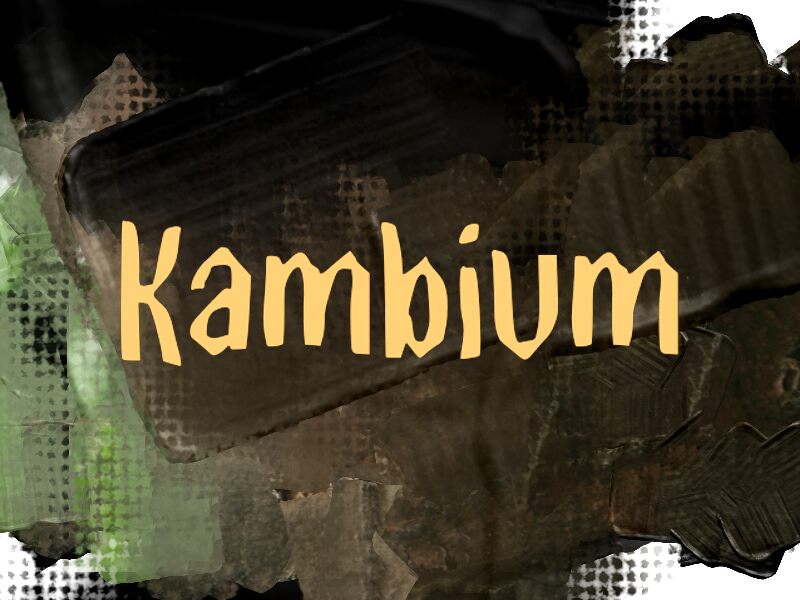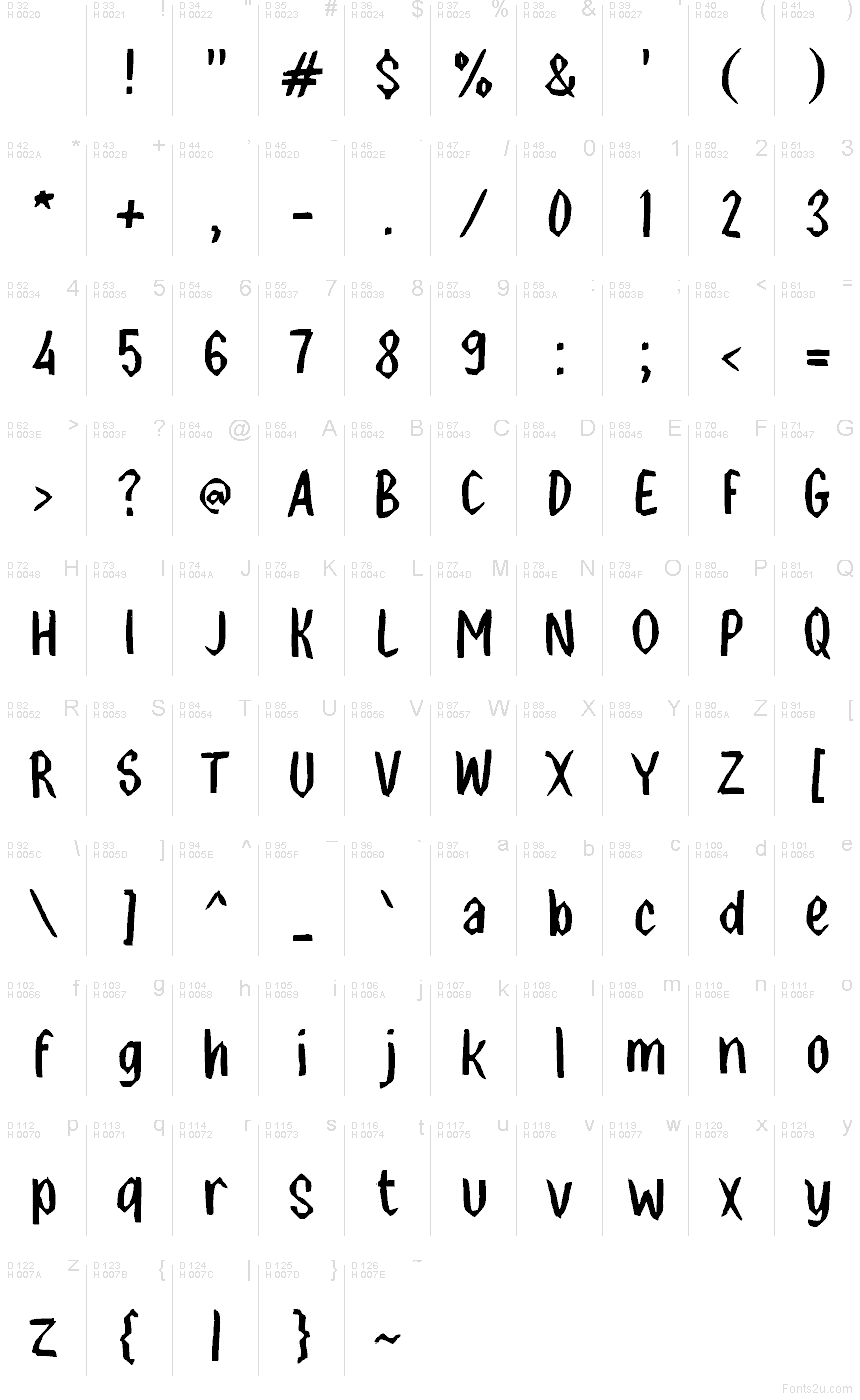
Kambium di Wep è un font display gratuito dall’aspetto ruvido, che evoca l'artigianato dell'intaglio su legno. Le lettere sono alte, strette e leggermente irregolari; con le sue tacche affilate e i tratti verticali massicci, l'intero font sembra scolpito piuttosto che disegnato.
Questo rende Kambium ideale per poster, copertine di libri indie, titoli di giochi, intestazioni di zine e branding rustico, dove serve un font gratuito che abbia più carattere che perfezione. È perfetto anche per brevi testi su packaging o grafiche di eventi, perché il ritmo irregolare e artigianale dona un tocco tattile e leggermente grezzo, anche a poche parole.
Kambium
Presentazione e campione visivo del carattere Kambium